간판 역사 100년, 진귀하고 흥미로운 이야기_2.현대 간판디자인
<간판 역사 100년전>이 근현대디자인박물관 개관 4주년 기념 특별전으로 기획되어 선보였다. 전시는 크게 다섯 부분으로 나뉘어져 한 달간 진행되었다. 제 1파트에서는 60여장의 사진 속에 나타난 초기 간판의 모습을, 제 2파트에서는 일제강점기부터 현대에 이르기까지 박물관에서 소장하고 있었던 실제 간판 약 170여종이 전시되었다. 제 3파트에서는 서울의 대표 거리 다섯 곳의 거리 간판 풍경전을, 제 4파트에서는 전문디자이너들이 참여한 10대 도시 간판디자인 초대전이 펼쳐졌다. 1960년대 거리를 재현해 기념사진을 촬영할 수 있도록 꾸며지기도 했다. 전시는 마무리되었지만, 박물관 측 협조로 폰트클럽에 전시 내용 중 일부를 소개한다.
10대 도시를 디자인하다
간판은 단순한 상업적 목적을 벗어나 현대 도시 공공디자인의 중요한 수단으로 자리잡았다. 각 지방의 특색에 맞는 간판디자인 문화를 정착시키기 위한 작은 시도와 노력의 일환으로, <간판역사 100년전>에서는 현재 활동중인 디자이너 10인을 초대, 국내 대표 10대 도시를 선정하여 각 도시 컨셉 및 슬로건에 맞는 아름다운 한글 간판을 디자인해 선보였다. 참고로, 10대 도시(서울, 부산, 인천, 대전, 대구, 전주, 경주, 광주, 울산, 제주)는 인구수를 기본으로 하여, 도시의 뚜렷한 특징이 도드라지고, 국내외 관광객 유동이 많아 간판활용 및 쓰임이 많은 대표 도시로 선정되었다. 작품은 도시명 가나다 순서로 소개한다.
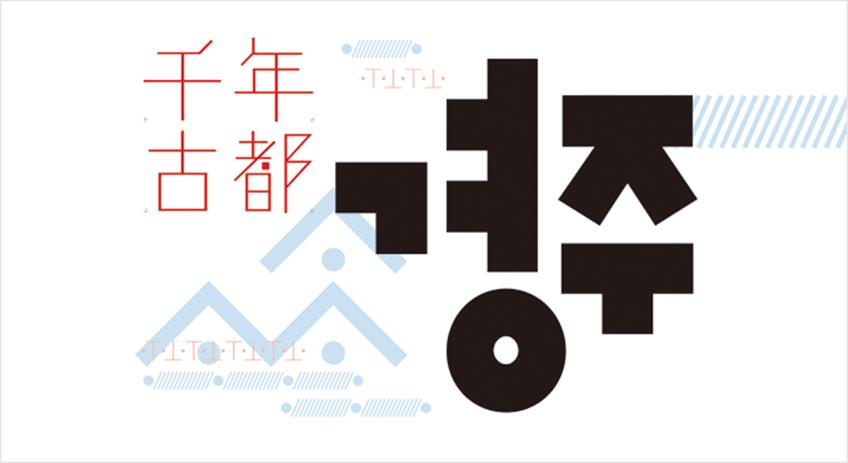
경주_김희준
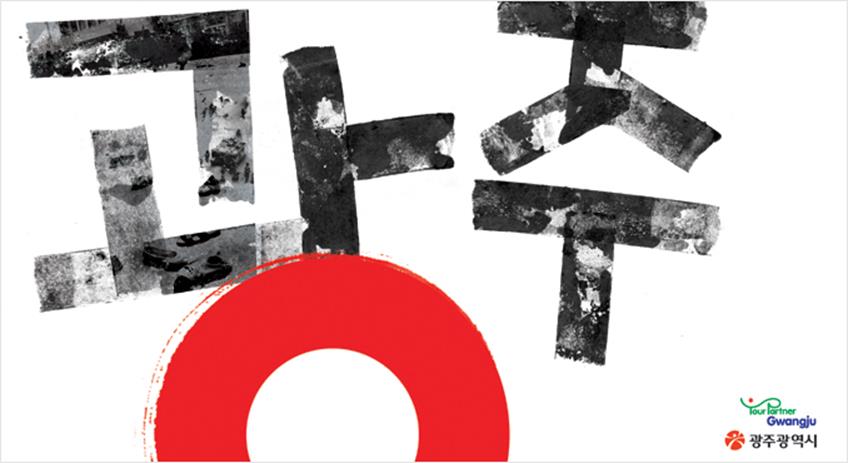
광주_모은영
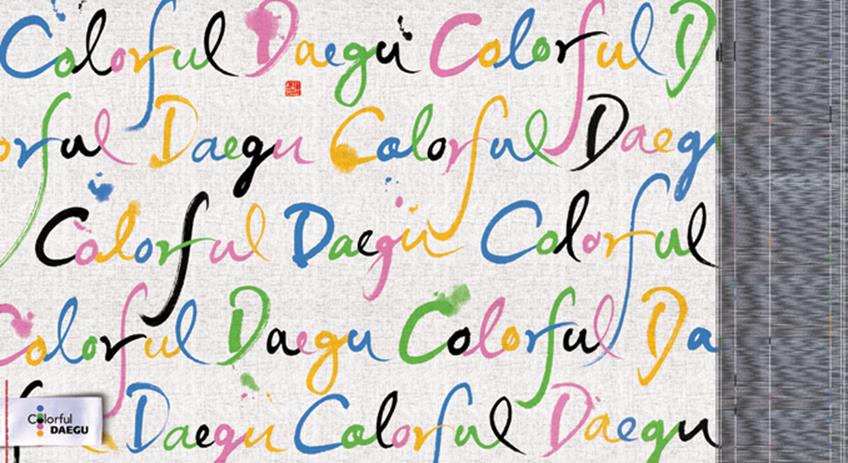
대구_이승환
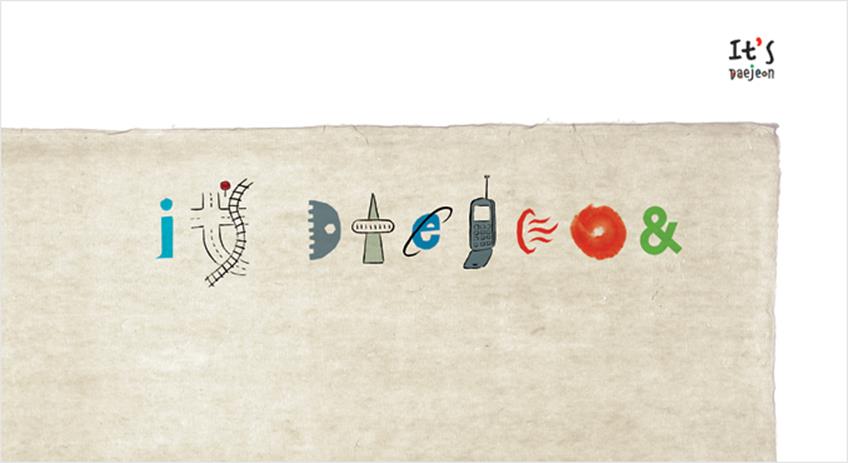
대전-최일섭
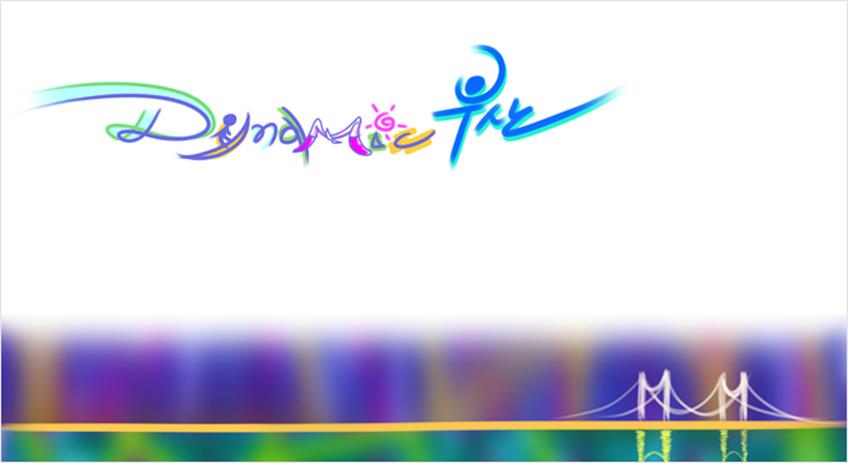
부산_김재현
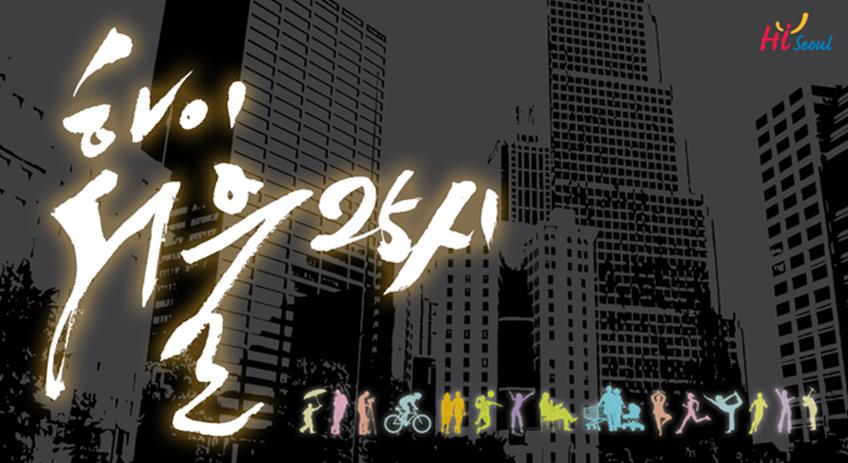
서울_박암종
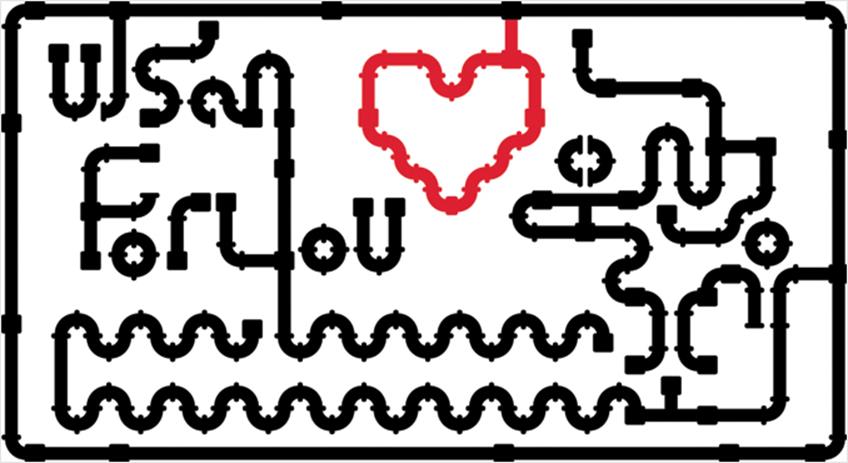
울산_이호
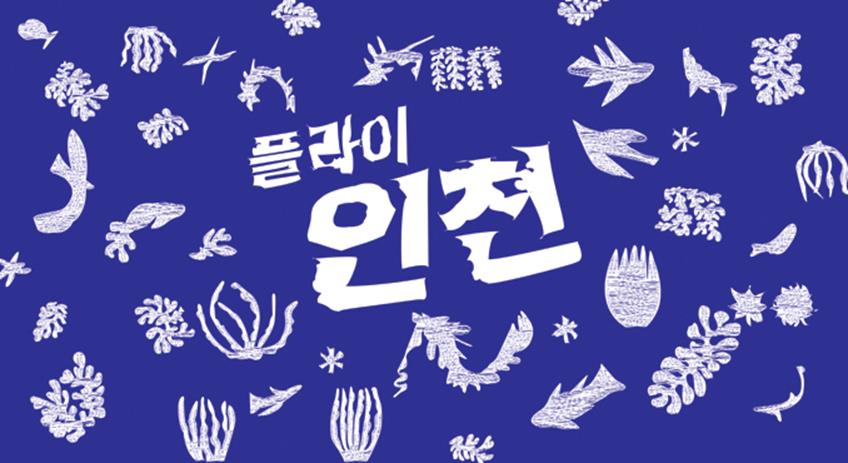
인천_안병국
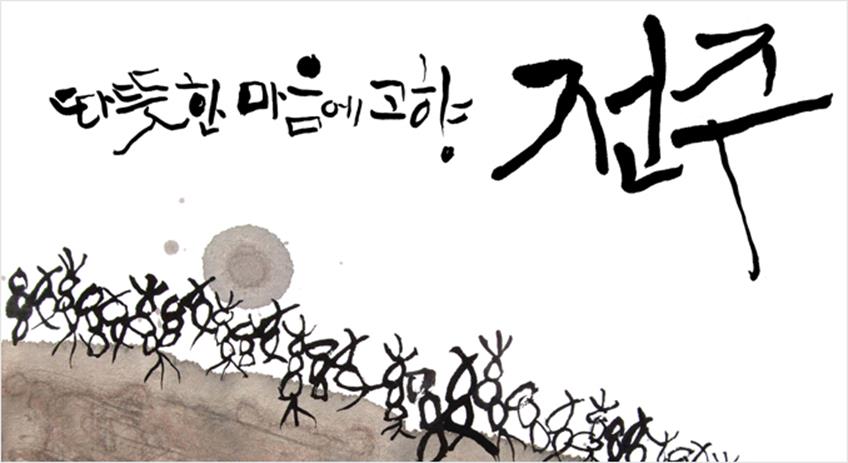
전주 _오민준
제주_이상현
지금 간판 하러 갑니다
간판의 아름다움이란 단순히 상점, 상품만의 아름다움을 의미하는 것이 아니다. 그 상점 또는 상품의 광고효과에 앞서 도시 환경의 아름다움을 도울 수 있는 미적 측면에서도 다루어져야 한다. 2012년 9월, 현재의 간판은 과연 어떠한 모습일까? 홍대앞, 강남역, 압구정, 종로, 인사동 등 서울시내 주요 명소 다섯 군데의 간판 현황을 기록하기 위해 선문대학교 시각디자인학과 대학생들과 공동작업(Collaboration Project)을 진행해 선보였다. 17인의 젊은 대학생들과 함께 그들의 눈에 비친 현대 도시의 간판들이 사진과 동영상으로 기록되었다.
부록_ 간판이야기
100년 전 한반도에 펼쳐진 석유 전쟁
저녁이 되면 우리는 칠흑 같은 어두움을 만난다. 이 어두움을 이겨내는 방법은 불을 피우는 것인데 오늘날에는 전기가 있어 스위치만 올리면 불을 밝힐 수 있으나 예전에는 호롱에 기름을 붓고 불을 밝혔다. 자연산 기름은 얻기도 힘들거니와 밝기도 그리 밝지 않아 매우 불편하였다. 그래서 석유가 수입되었다. 일제 강점기 우리나라에 수입되어 판매된 석유는 여러 가지였다.
런던표 쉘 석유 간판
1920년대 l 법랑 l 45.4×50.4cm
근현대디자인박물관 소장
런던표 쉘 석유광고용 간판으로서 조개모양을 한 특이한 간판이다. 영국의 쉘 석유회사에서 생산하는 석유를 공급하는 대리점에 배포한 간판으로서 미국의 텍사코 T 회사의 석유제품과 경쟁을 벌였던 회사의 간판이다.
텍사코 별표 간판
1920년대 l 법랑 l 44.5×34.6cm
근현대디자인박물관 소장
미국 텍사코 별표 석유광고용 대리점 간판으로서 한쪽 면을 빼서 벽에 붙일 수 있게 제작되었다. 앞면은 한자와 일어로 되어 있으나 뒷면은 한글을 넣어 누구나 쉽게 읽을 수 있게 하였다.
일제 강점기에 제작된 석유 간판이 여러 개 남아있다는 것은 그만큼 공격적인 판매를 했다는 것이고, 또한 많은 곳에서 판매를 했다는 증거일 것이다. 수익성도 높았다고 봐야 한다. 석유회사가 여럿 들어와 각축을 벌였다. 지금도 있는 텍사코, 쉘 석유간판이 유난히 눈에 띈다. 일제에 의해 국권이 피탈되자 국치를 통분해 절명시 4편을 남기고 음독 순국한 황현(黃玹: 1855~910). 그의 한말 풍운사를 담은 <매천야록(梅泉野錄)>에는 다음과 같은 기록이 있다.
“석유는 영국이나 미국 같은 서양에서 나온 것이라 한다. 어떤 사람은 바닷 속에서 난다고도 하고, 혹은 석탄으로 만든다고도 하고, 혹은 돌을 삶아서 그 물을 받은 것이라고도 하여 그 설이 다르다.(중략) 우리나라에서는 경진년 이후 처음으로 사용되었다. 처음에는 그 색깔이 불그스레하고 냄새가 심했으나, 한 홉이면 열흘을 밝힐 수 있었다.”
이 기록을 토대로 하면 우리나라에서 처음으로 석유가 사용된 때는 고종 17년, 경진년인 1880년이다. 개화파 인사들이 일본에 건너가 서양 문물을 구경하다 석유와 석유 램프, 성냥 등을 갖고 귀국하면서 우리나라 에너지산업은 태동했다. 석유가 들어오기 전 국내에서는 식물성 원료인 아주까리나 송진을 이용해 등잔불을 밝혔다. 조미 수교 2년 뒤인 1884년 미국에서 석유가 대량 수입되기 시작하면서 1890~1900년대에는 광목류와 함께 국내 수입 1~2위를 다퉜다.
개화기 때 미국 공사 알렌은 1898년 서울시 가로등에 석유를 사용해 불을 밝혔다고 기록했다. 당시 국내에는 자동차가 많지 않아 등유, 휘발유 등의 구분 없이 ‘석유’라는 명칭을 썼다. 1897년 알렌은 우리 정부로부터 석유와 관련된 이권을 대거 따냈으며, 미국 최대 석유회사였던 스탠다드오일에 ‘솔표’라는 상호를 붙여 석유를 독점 판매했다. 스탠다드오일은 경성과 인천 등을 상대로 무역업을 하던 미국인 타운센트에게 국내 유일의 대리점 영업권을 주었으며 그는 인천에 ‘순신창’이라는 석유 판매 대리점을 내 큰돈을 벌었다. 스탠다드오일은 1920년대까지 국내 석유시장을 독점했다.
승리표 SOCONY 석유광고 간판
1920년대 l 법랑 l 지름 45cm
근현대디자인박물관 소장
미국 스탠다드 석유회사에서 발매한 승리표 SOCONY 석유 광고용 간판이다. 디자인이 복잡하지만 나름대로 의미를 담아 디자인하였다. SOCONY라는 의미는 뉴욕에 있는 스탠다드 석유회사(Standard Oil Co. of New York)라는 단어의 이니셜이다.
미국 텍사코와 영국 셸(Shell)이 들어오면서 이미 들어와 영업을 하고 있던 스탠다드오일과 치열한 3파전이 벌어졌다. 당시 스탠다드오일은 승리표, 텍사코는 별표, 셸은 조개표라는 브랜드를 달고 영업했다. 1935년 일본에서도 조선석유회사를 설립하고, 30만 톤(6000배럴) 규모의 원산 정유공장을 짓고 미국으로부터 원유를 들여와 정제한 후 판매하였다. 당시 판매를 대행한 업체가 미스비시상사회사였다. 태평양 전쟁이 발발하기 이전 치열한 석유전쟁이 이 한반도에서 있었던 것이다